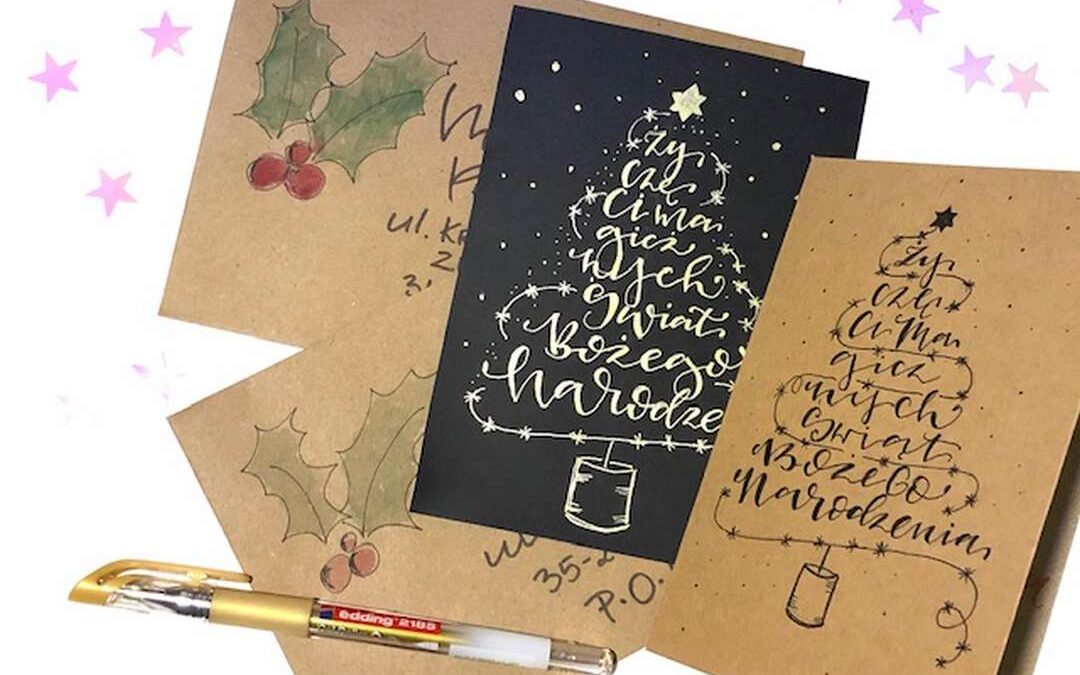
Jak wykonać kartkę świąteczną „choinka” -szablon
Kartka świąteczna letteringowa choinka
Kartka „świąteczna choinka” to prosty, ale zarazem piękny projekt, który wykonasz w kilka minut i z pewnością zaskoczysz swoich bliskich.
Do wykonania potrzebujesz
-dwa cienkopisy o różnych grubościach końcówek, np. Tombow 01 i 03 lub stabilo F i M
-jasny papier lub brązowy, np. Mondi 100g, lub inny w formacie A6
-ciemny papier np. Clairefontaine format A6
-połyskujące markery (srebrny lub złoty), np. edding markery olejowe grubość 2 mm lub edding żelowy długopis: wykonamy nim oszukaną kaligrafię
-ołówek, gumka, ekierka
Krok 1
Narysuj najpierw ołówkiem zarys kompozycji pod lettering w formie choinki. W tym celu nakreśl ołówkiem linię prostopadłą na środku kartki z odstępem 3,5 cm od góry i 2 cm od dołu. Na wysokości 3,5 cm –licząc od dołu narysuj linię równoległą, a następnie w odstępie 1 cm dorysuj 6 pozostałych liń, skracając każdą kolejną o 0,5 cm z prawej i lewej strony.
Krok 2
Wykonaj ołówkiem lettering zaczynając od pierwszej linii. Staraj się połączyć większe oraz mniejsze litery ze sobą- Twoja kompozycja będzie jeszcze ciekawsza, ponieważ mix kilku stylów wygląda kreatywnie.
Krok 3
Popraw teraz wszystkie literki cienkopisem (najlepiej tym cieńszym w rozmiarze F). Poczekaj, aż cieńkopis wyschnie i wymaż pozostałości ołówka.
Poprawiamy ołówek cienkopisem
Krok 4
Zastosuj teraz technikę oszukanej kaligrafii tzn. wymaluj od środka wszystkie linie w literach, które idą w dół. Twój lettering jest teraz jeszcze piękniejszy.
Krok 5
Cienkopisem w rozmiarze M dorysuj lampki ze światełkami oraz gwiazdkę na czubku choinki. Na sam koniec narysuj małą doniczkę.
Drzewko na czarnym papierze
Spróbuj wykonać podobny napis na czarnym papierze, wykorzystując w tym celu złoty żelowy długopis edding. Tym razem nakreśl ołówkiem same punkty, w których będzie się zaczynał i kończył Twój lettering. Jeśli nie czujesz się na tyle, aby pisać od razu żelopisem, nakreśl literki delikatnie ołówkiem. Gdy będziesz je poprawiać złotym kolorem, staraj się idealnie pokryć ołówek, poniważ nie będziesz musieć go wymazywać. Na koniec zastosuj technikę oszukanej kaligrafii oraz dorysuj lampki, gwiazdki oraz doniczkę.
złoty napis na czarnym papierze
Gotowe! Podaruj bliskiej Ci osobie te świąteczne wyjątkowe życzenia! Z pewnością wywoła ona uśmiech na jej twarzy.
inny przykład kartki, tym razem biały napis